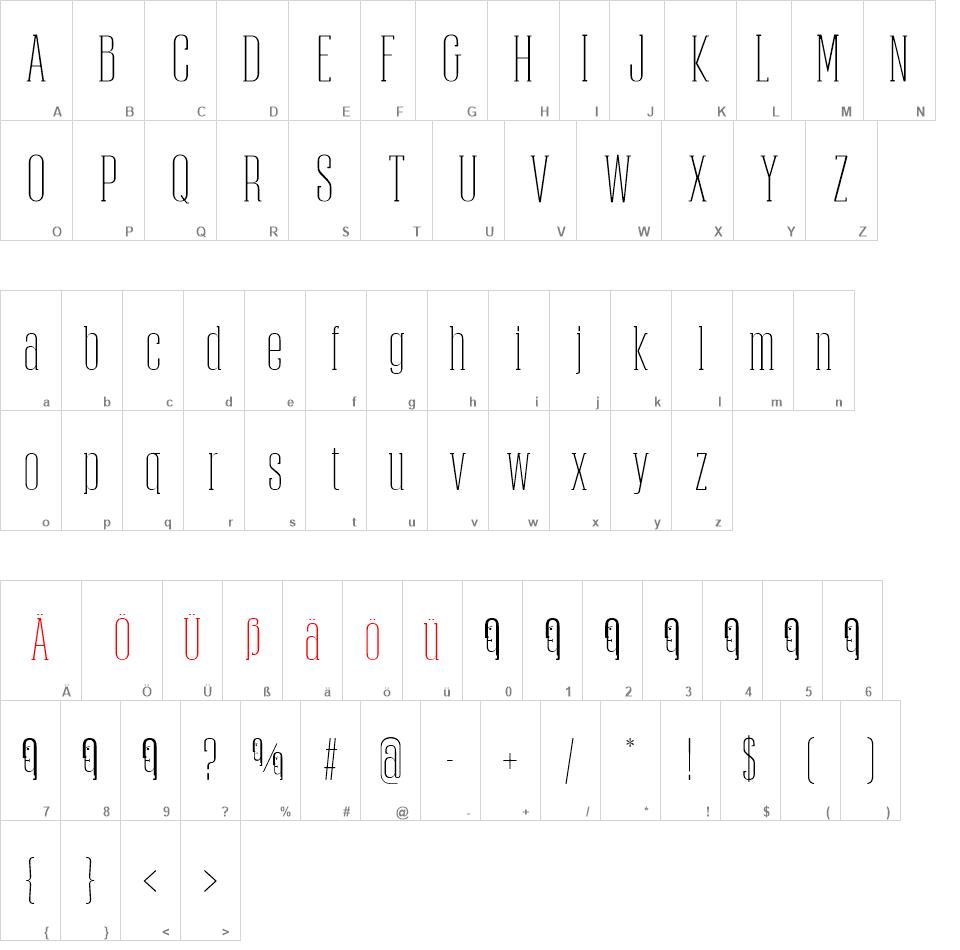
Obcecada Serif Font
Obcecada Serif, sehr konzentrierte, geometrisch dünn beschichtete runde Billet-Hörner und -gelenke sind kurze Schriftzüge und kurze Tropfen.